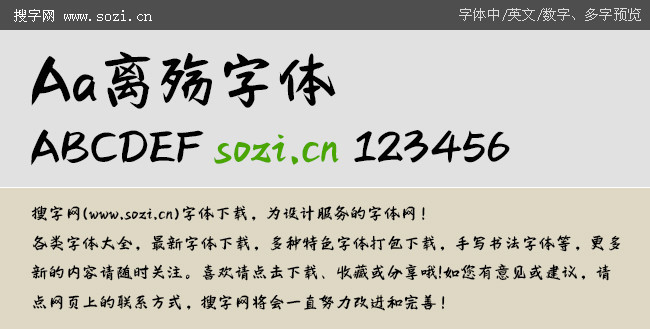
Aa離殤字體
搜字網(wǎng)給大家提供一款A(yù)a離殤字體中文卡通字體下載,這是一款手寫風(fēng)格的書法字體,字體書寫自如,效果瀟灑大方,適合海報(bào)設(shè)計(jì)、包裝畫冊等宣傳廣告等應(yīng)用(此字體為個(gè)人非商用版,如需商用請聯(lián)系作者購買版權(quán))。